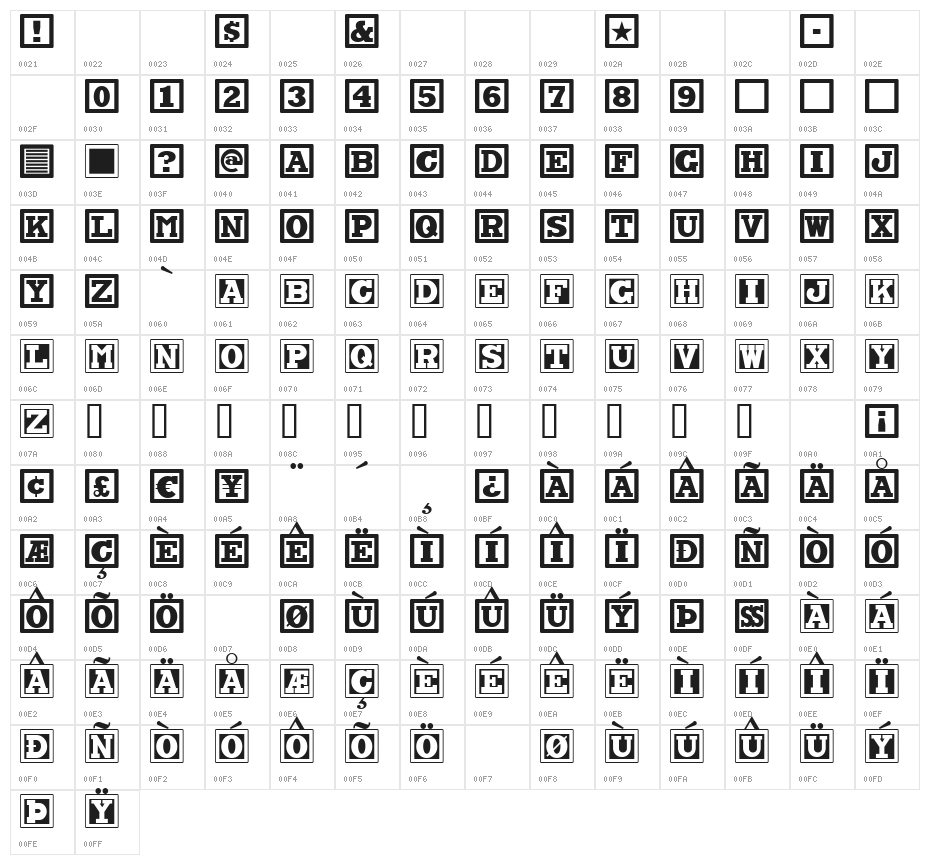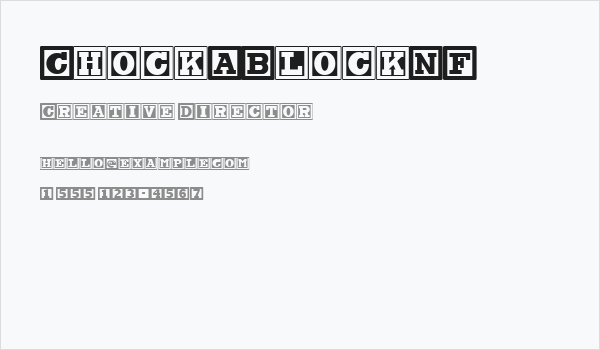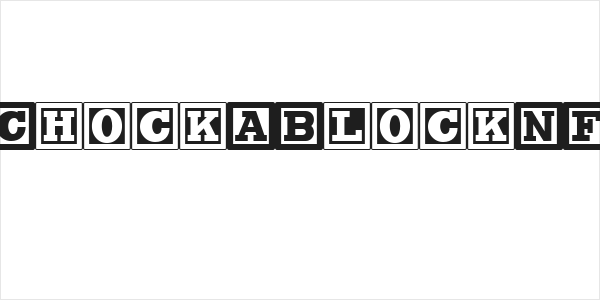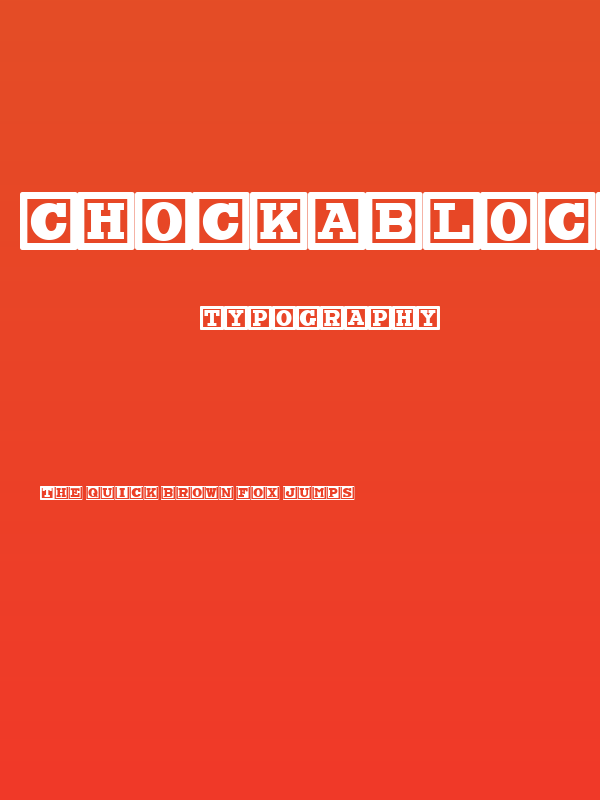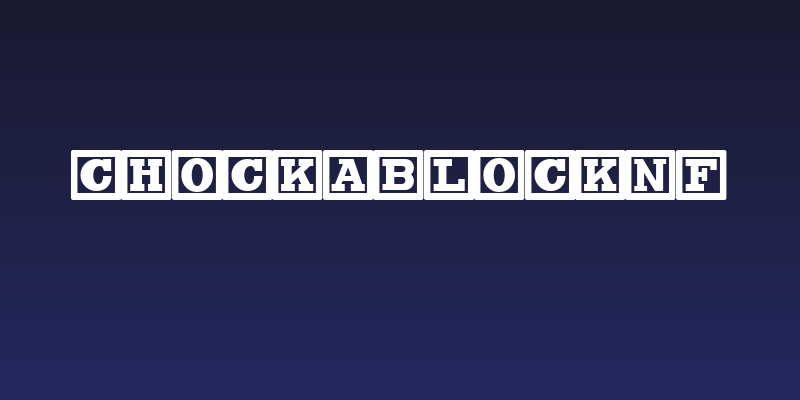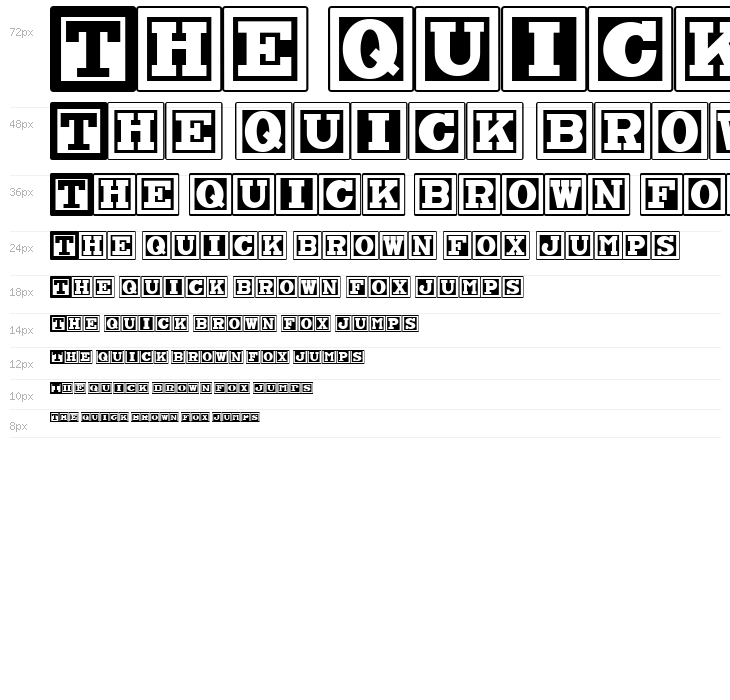
ChockABlockNF Font
| Stile generale | Vintage, Modern |
| Progetti proposti | Ideal for poster designs, branding projects, and any creative work that requires a bold statement. It can also be used for packaging, signage, and editorial design where a distinctive look is desired. |